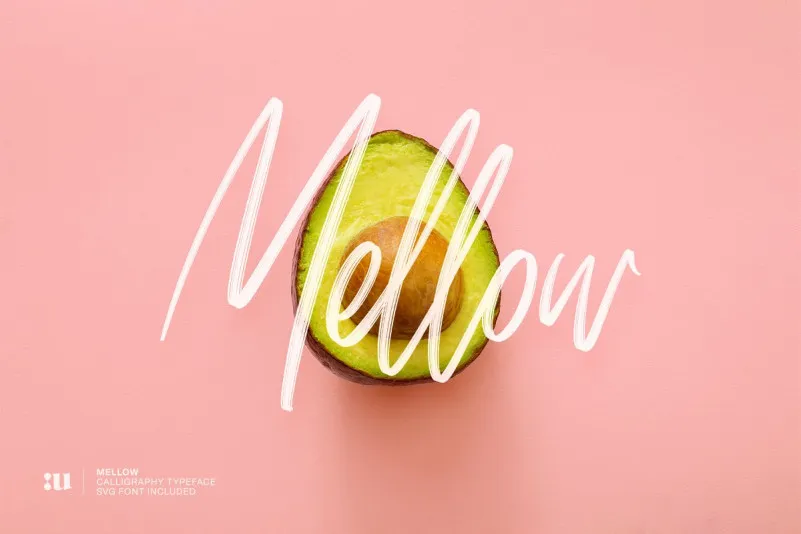
Mellow Brush SVG Font – Download Grátis
Esta fonte gratuita é uma mistura de brush e SVG, projetada para dar um toque autêntico à sua arte manual. Introduzimos a Mellow Font, uma fonte feita à mão que se assemelha a escrita tipográfica realista, disponível nas duas formas: SVG e Brush. Esta font versátil pode ser usada em uma variedade de projetos design, como identidade, papelaria, logotipos, citações, capas de revistas ou livros, cabeçalhos de websites, roupas, marcação e embalagens. “Mellow Brush” é perfeitamente adaptado a várias finalidades do design, desde assinaturas até embalagens, logos para lojas online, tags de produtos e mais. Com esta fonte, você adicionará um toque único à sua arte digital, transformando seus designs em algo autêntico e realista. Seja você um designer profissional ou iniciante, Mellow Brush é uma opção excelente para introduzir um pouco de personalização ao seu trabalho de design.